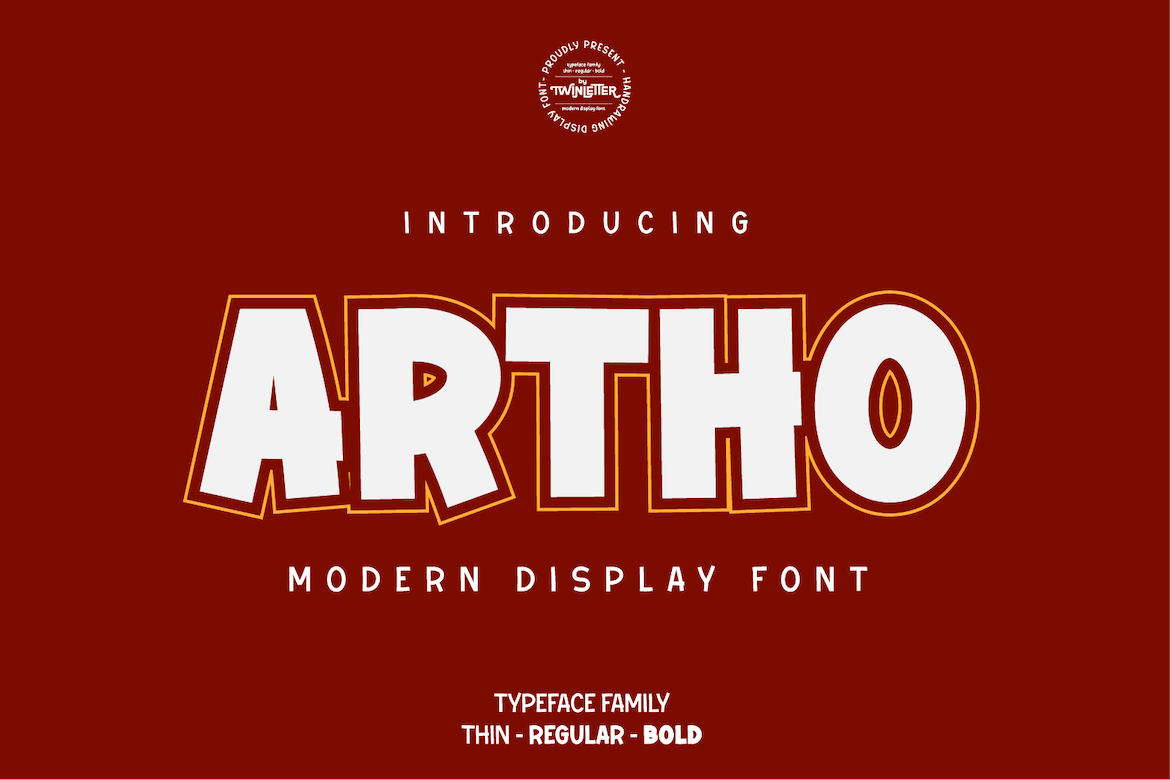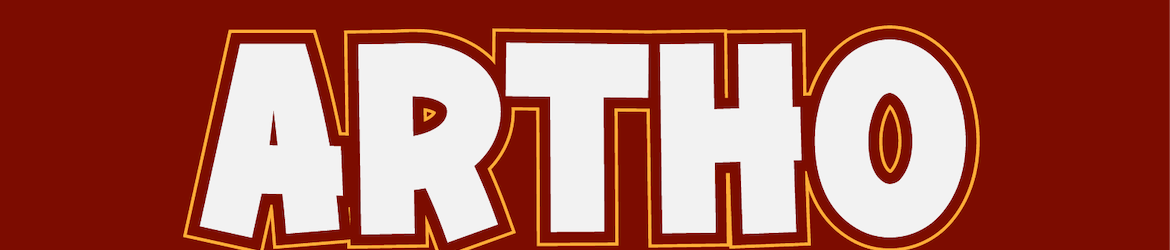
A Artho Font é uma elegante escolha para designers visuais que valorizam personalidade e destaque. Desenvolvida por twinletter, esta fonte de display tem um tom forte e expressivo, ideal para criar texturas impactantes em qualquer projeto gráfico. Seja ela o centro do design ou apenas complemento, Artho é uma opção perfeita para quem busca adicionar profundidade visual aos seus projetos. Conhecida por seu formato robusto e atraente, essa fonte se destaca quando usada em headlines, marcas de texto ou qualquer outro conteúdo que precisa ser o foco. Suas letras amplos fazem com que ela seja uma excelente opção para criar texturas impactantes e estilos que chamam atenção. Com uma grande capacidade de personalização, a Artho é ideal tanto para designers gráficos quanto para pessoas que desejam dar um toque único em seus próprios projetos pessoais. Quando se trata de adicionar destaque aos seus materiais digitais, o design da Artho representa um investimento inteligente. Essa fonte oferece uma variedade impressionante de opções para personalizar seu estilo gráfico, tornando-a uma escolha ótima para quem busca dar vida a suas criações visuais de forma única e autêntica.